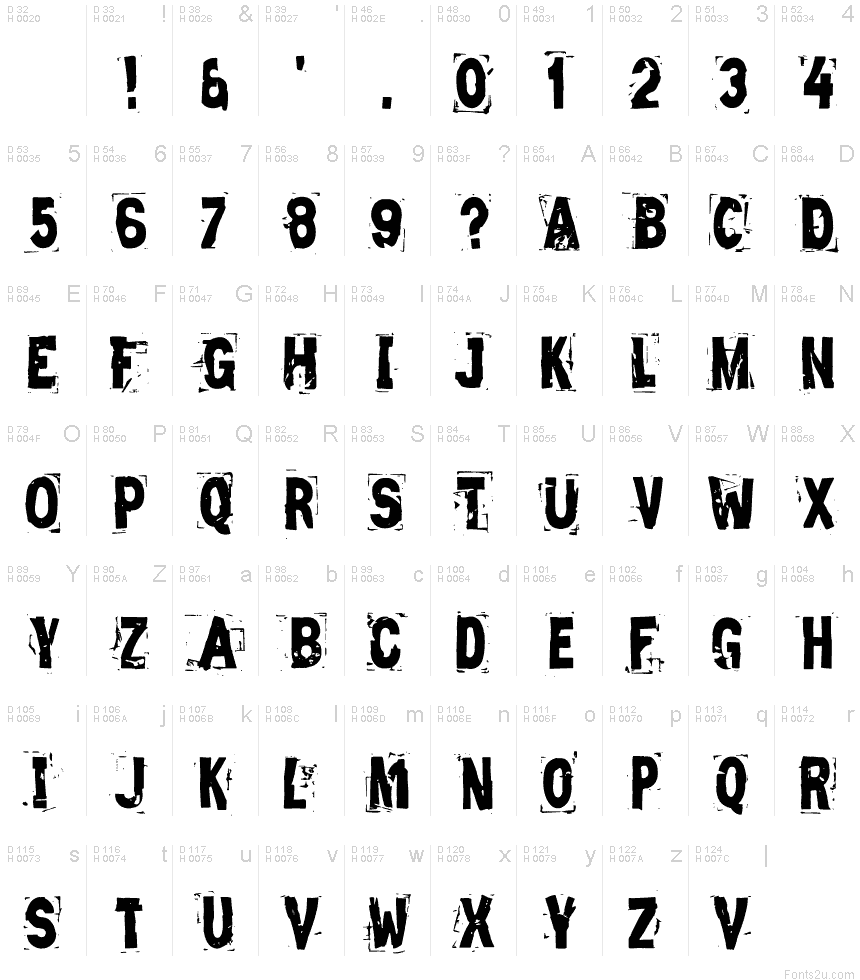
Zero & Zero Is autorstwa Vica Fiegera to bezpłatny, erodowany krój typu display, utrzymany w estetyce postrzępionych plakatów. Wielkie litery są ciężkie i surowe, a ich krawędzie – podrapane, wyszczerbione i nierówne – nadają im uliczny, „ręcznie rwany” charakter, daleki od sterylnej geometrii.
Dzięki tak szorstkiej sylwetce krój ten świetnie sprawdza się w zinach, ulotkach koncertowych, tytułach filmów niezależnych, plakatach protestacyjnych i nagłówkach, które wymagają buntowniczego, improwizowanego wyrazu. Jako bezpłatny font, najlepiej działa w krótkich formach – nagłówkach, projektach logo czy monogramach – gdzie popękane narożniki i przetarte krawędzie mogą w pełni pokazać swój charakter.